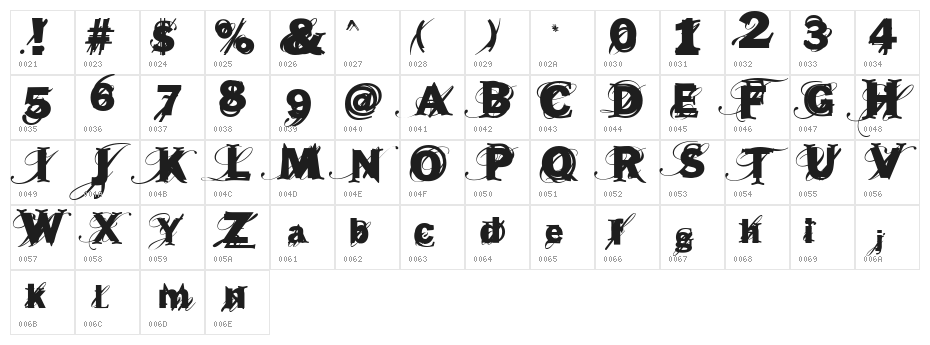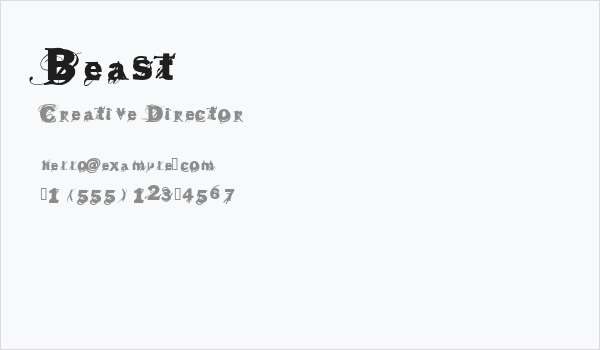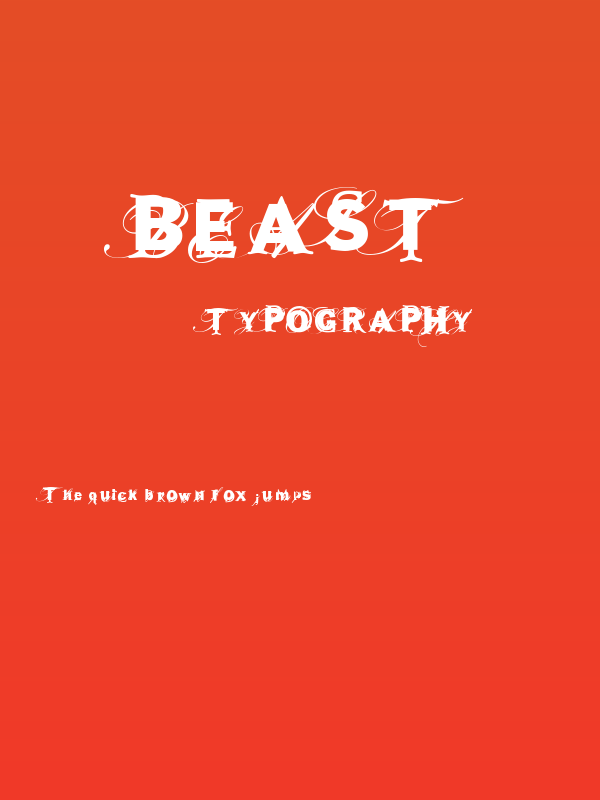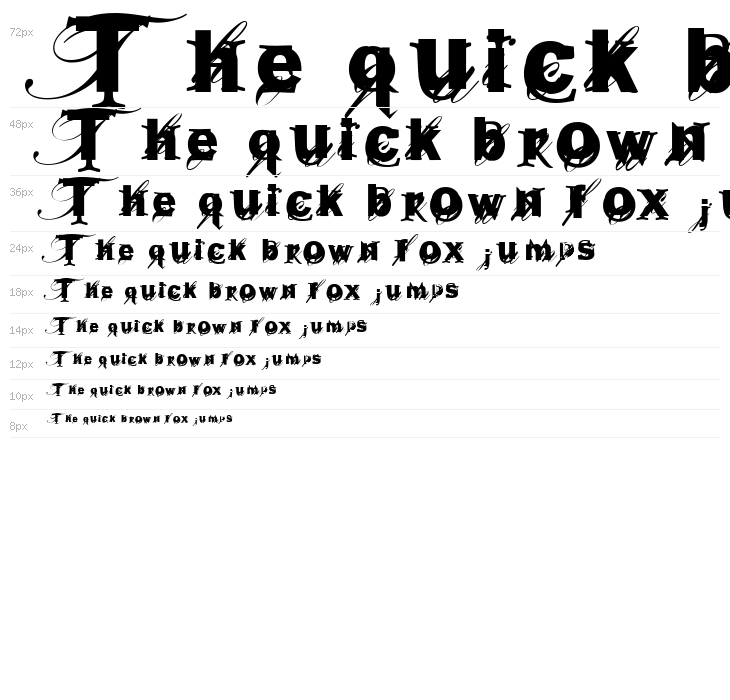
Beast Font
✎ Crazy
| Vorgeschlagene Projekte | Ideal for album covers, posters, branding for edgy or gothic-themed products, and any design requiring a dramatic flair. |